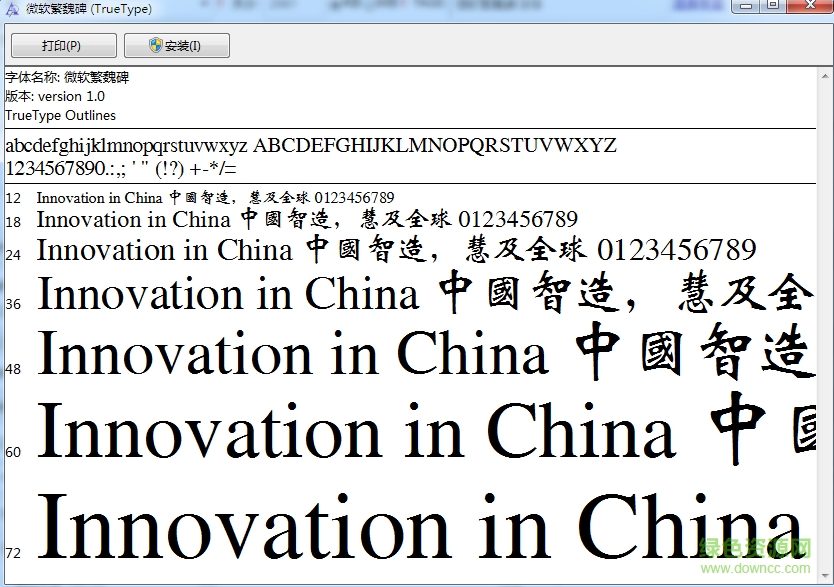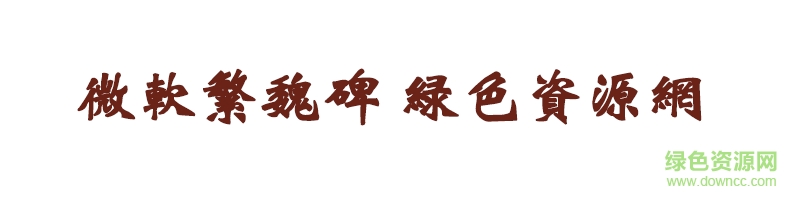
微軟繁魏碑是一款根據(jù)中國書法魏碑體制作的一款電腦字體,突出的特點是撇捺向兩側(cè)伸展,收筆前的粗頓以及抬峰,使整個字形厚重穩(wěn)健略顯飛揚、規(guī)則中正而有動態(tài),頗具審美價值。喜歡可以來綠色資源網(wǎng)下載!
微軟繁魏碑字體是一款字形有沒的電腦字體,保持了魏碑體橫畫和捺畫保持隸書的特點,常伸展到字形邊界甚至超出邊界;字形與隸書相比呈扁方形的特點!